Cara Memilih Font Tepat Untuk Website Bisnis Anda
Memilih font untuk header dan font untuk body dengan tepat benar-benar penting bagi keseluruhan desain website bisnis anda. Meskipun tipografi sering diabaikan, namun memilih jenis huruf yang tepat dapat membuat perbedaan besar untuk kinerja halaman web. Memilih font yang sesuai secara substansial akan meningkatkan daya tarik website dan akan menarik lebih banyak pelanggan anda.
Mengapa Memilih Font itu Penting?
Dalam bisnis online anda tentunya selain memaparkan gambar anda juga menyajikan tulisan, maka dari itu pemilihan font yang tepat adalah keharusan. Berikut beberapa alasan kenapa Font begitu penting untuk situs anda :
- Dapat mempengaruhi merek
- Refleks pada pembacaan yang baik
- Menarik pengunjung
- Memperkuat pengalaman pengguna
- Membantu navigasi situs
- Memastikan keamanan web dan visibilitas di semua browser dan perangkat
Dalam artikel ini saya akan memberikan beberapa pedoman umum memilih jenis huruf yang tepat untuk setiap website profesional:
1. Keterbacaan
Tidak ada gunanya dalam menciptakan konten yang besar jika tidak dapat dengan mudah dikonsumsi oleh pengunjung situs anda. Sebuah tipografi yang terpilih dengan baik adalah salah satu langkah paling penting dalam arah ini. Pastikan font yang anda pilih cukup terbaca. Semakin sederhana semakin baik.
Font Rumit mungkin terlihat lebih menarik dan elegan tapi font dengan model seperti itu tidak cocok untuk dipasang dibagian body, pilihlah font yang sederhana tapi mudah untuk dibaca akan menjadi langkah bijaksana untuk mengesankan dan mempertahankan pengunjung anda berlama-lama di situs anda. Hindari naskah atau tipografi dekoratif jika anda tidak ingin pengunjung anda segera meninggalkan situs anda.
Untuk pemilihan ukuran font, banyak situs memilih font dalam kisaran 10px – 12px. Untuk mencapai pembacaan yang optimal dengan menggunakan ukuran font minimal 14px- 16px lebih dianjurkan. Ketika anda ingin memutuskan berapa ukuran font untuk judul anda, pilihlah ukuran yang besar dan jelas, hal itu untuk membedakan antar judul dan isi.
2. Kombinasi
Sebagian besar desainer profesional menggunakan dua tipografi: satu untuk bagian body dan satu Title atau judul. Alasan menggunakan lebih dari satu adalah agar menghindari kesan monoton dan meningkatkan efek visual tetapi juga untuk meningkatkan hirarki konten dan membuatnya lebih jelas. Meskipun jumlah font yang dipilih itu terserah anda, tapi alangkah baiknya jika anda cukup menggunakan dua atau tiga font.
Ketika mengambil sepasang font, hal yang paling penting untuk dipertimbangkan adalah bagaimana kedua font bekerja sama. “Apakah mereka cukup mirip?”, “Mungkin terlalu mirip?”, “Apakah mereka bentrok?”, “Apakah mereka terlalu berbeda?”, “Apakah mereka saling melengkapi?”. Coba mereka semua jika diperlukan dan mengeksplorasi semua alternatif yang mungkin. Itulah cara yang paling efektif untuk mengetahui kombinasi yang paling kuat untuk halaman Web Anda.
Sebuah contoh yang baik adalah memilih Strong Sans-Serif untuk judul utama, dan Serif sederhana untuk lainnya. itu adalah cara sederhana dan terlihat melengkapi.
3. Familiar dengan Font Utama
Ada empat kategori utama font yang perlu Anda ketahui:
Serif Font : Font ini datang dengan tanda garis kecil yang menghiasi ujungnya. Font Serif dapat digunakan untuk blok yang lebih besar dari body. Font ini mempunyai karakter yang lebih jelas dan lebih mudah dibaca di layar. Font Serif memberikan tampilan yang lebih formal, berkelas dan konservatif. Font Serif baik digunakan untuk pers tradisional, buku cetak, majalah dan surat kabar. Contoh Font Serif adalah seperti Time new Roman, Georgia.
Font sans-serif : Font ini sederhana dan mudah, Font ini merupakan bagian dari Serif Font, namun dengan namanya terdapat San yang artinya adalah tanpa, maka Font sans-serif ini tidak memiliki garis kecil di ujunga huruf. Font juga dapat digunakan untuk blok yang lebih besar dari body. Untuk Font ini terlihat lebih modern, mereka dianggap sebagai lebih informal, rapi dan menyenangkan. Tidak ada keraguan Font Sans-serif biasanya digunakan untuk headline koran digital, blog dan konten text situs.
Font Dekoratif : Font ini biasanya bertujuan untuk digunakan sebagai judul dan headline, dan kadang-kadang juga digunakan untuk sejumlah kecil teks yang perlu untuk terlihat dan menarik perhatian. Memberikan perasaan penting, aksen dan orisinalitas, font dekoratif sempurna dan cocok untuk kartu ucapan, logo dan poster.
Script Fonts : Font ini seperti tulisan tangan dan sebagian besar digunakan dalam undangan resmi, kutipan, logo, judul. Pilihan untuk menyorot teks tetapi sulit untuk dibaca jika disampaikan dalam jumlah besar. Script font menyampaikan sikap pribadi, kreatif dan artistik.
Infographic ini akan memberikan gambaran yang lebih jelas dari perasaan umum bahwa font yang berbeda digunakan untuk membangkitkan dalam pengguna:
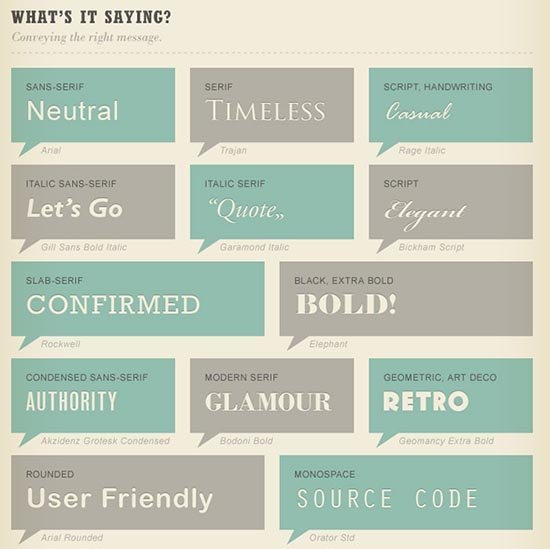
Dan itulah panduan lengkap cara memilih font yang tepat untuk website bisnis dan juga merek bisnis Anda. Semoga artikel ini bermanfaat buat Anda dan semoga bisnis Anda berkembang dan sukses.